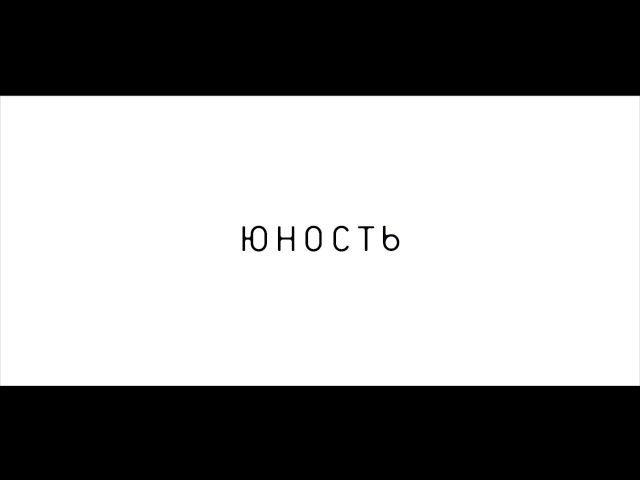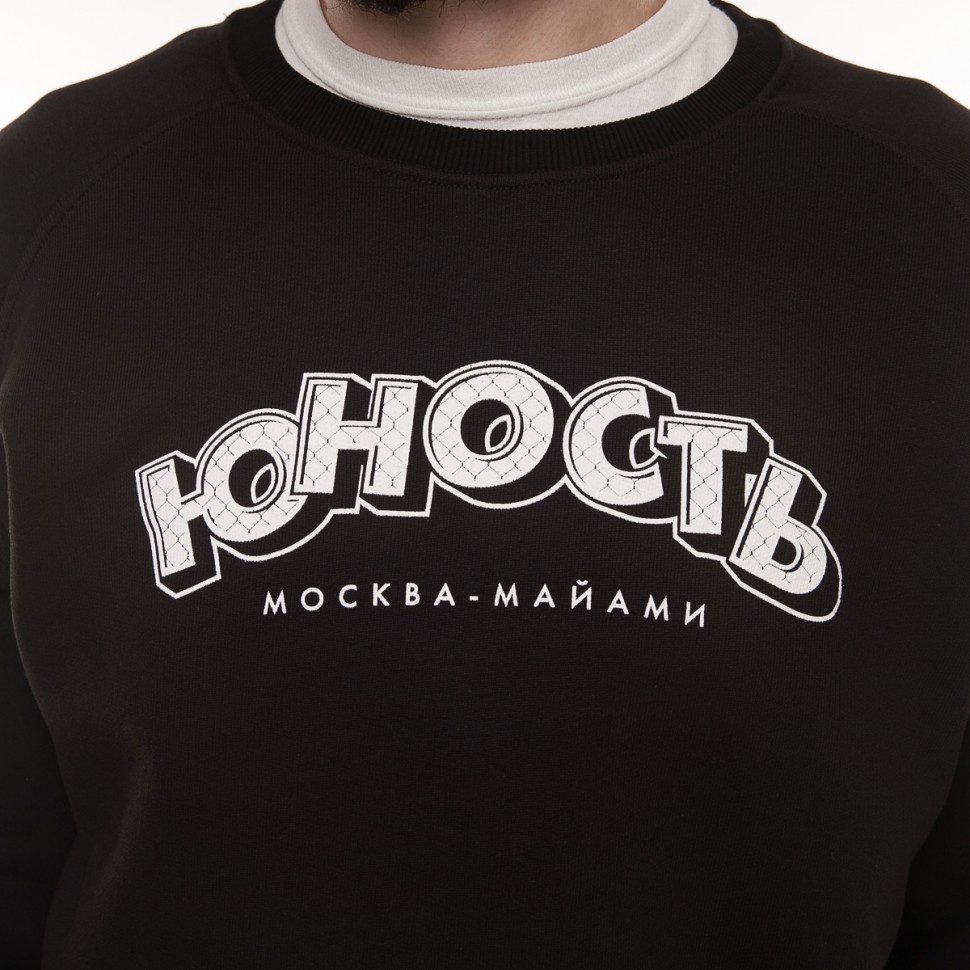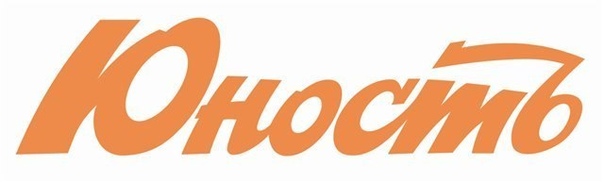
Надпись юность шрифт: Тату шрифты ONLINE подбор, красивые шрифты для тату надписей
Мне от моноширинных шрифтов многого не надо.
Адекватная поддержка кириллицы. Для программирования — отсутствие замыливания. Возможность различать 0 (который ноль) и О. Возможность различать I (которое i), l (которое L) и | (которое or). Для работы в консольном двухпанельнике — поддержка псевдографики. Однако в современном мире подобных шрифтов не так, чтобы много. Откуда же их взять?